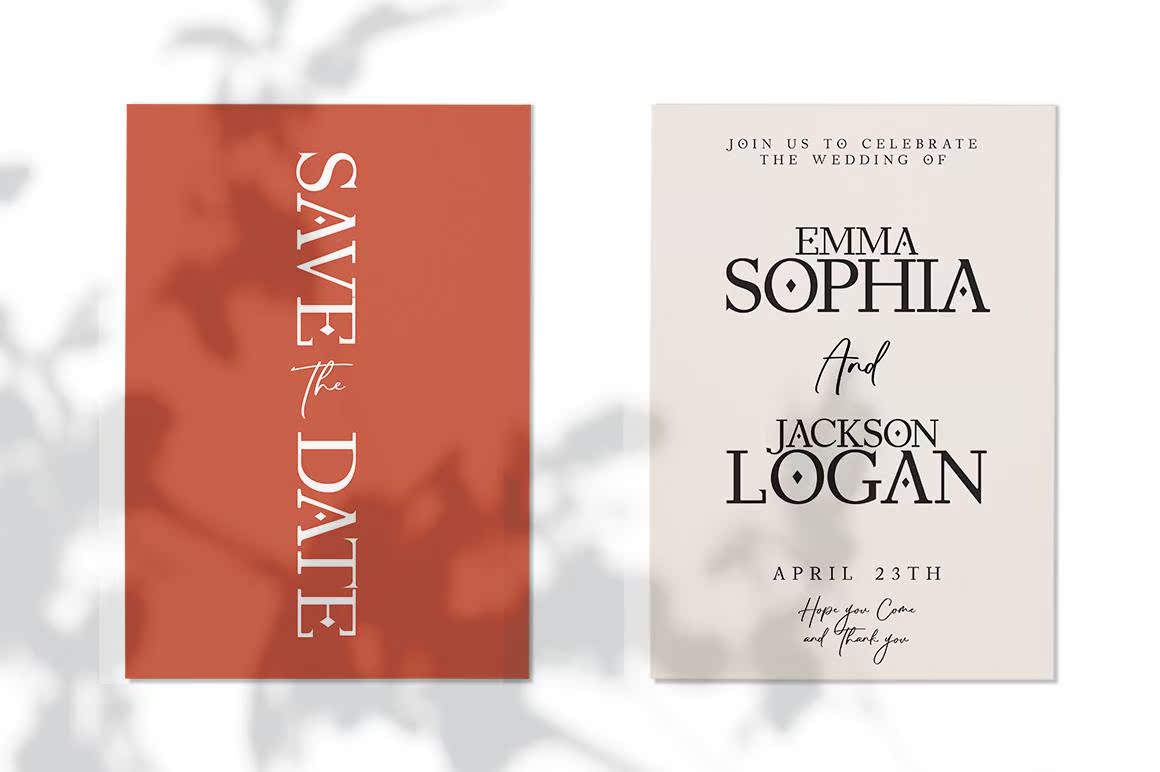
Black Pearl FontDuo,Scription and Serif,Luxury and Delege让您的项目看起来更漂亮、更好看,非常适合您需要LuxFeel的项目,因为这款Fonto的味道很好,每款Black Pearl FontDuo,Scription and Serif,Luxury Delege都有漂亮的检测和细节,让您的项目看起来更漂亮、更好看,非常适合您需要LuxFeel的项目,因为这是一种味道,每种味道都有很好的净化和细节